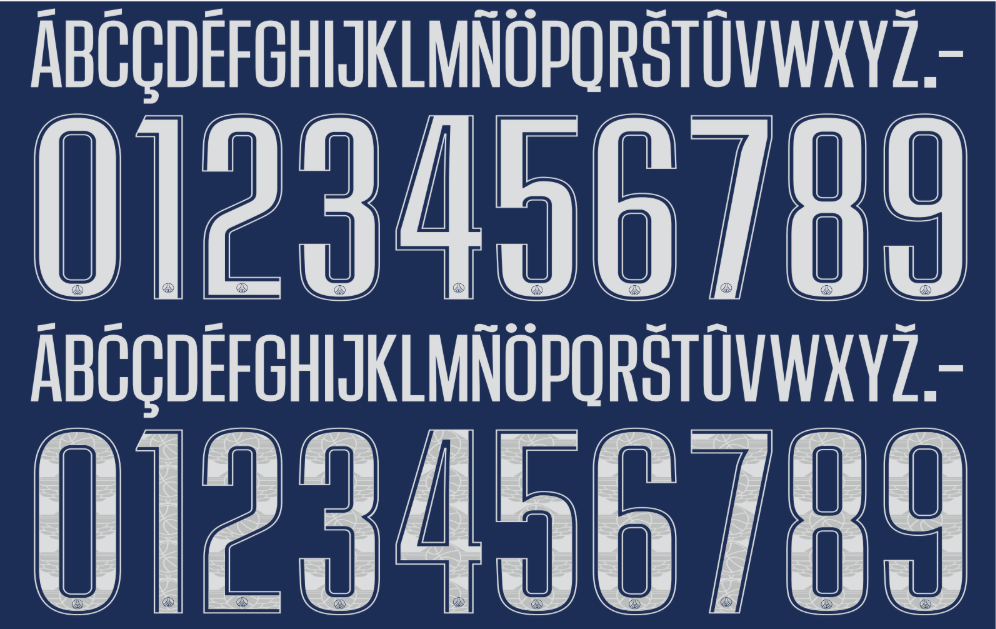
Paris não é apenas a capital da moda, é também o epicentro do estilo no futebol mundial. A nova temporada 2024-2025 traz o Paris Saint-Germain renovado, com uniformes que continuam a ditar tendências graças à poderosa parceria entre o clube, a Nike e a marca Jordan.
Se você trabalha com personalização de camisas, design esportivo ou modelagem 3D, ter a tipografia correta é obrigatório. Neste post, trazemos o arquivo da fonte oficial usada nos uniformes de jogo da Ligue 1 e Champions League, pronta para elevar o nível das suas criações.
Estilo Visual e Aplicação
A tipografia do PSG para esta temporada reflete a fusão entre o luxo e o streetwear, uma assinatura clássica da colaboração com a Nike. A fonte apresenta um design moderno, com caracteres levemente condensados e traços dinâmicos que sugerem velocidade e movimento.
Um destaque visual importante é a legibilidade à distância e o efeito de “recorte” em certos ângulos dos números, inspirados na arquitetura parisiense e na Torre Eiffel. Essa fonte é utilizada tanto no uniforme titular (Home) tradicional com a faixa Hechter, quanto nos kits alternativos assinados pela Jordan Brand. É a escolha perfeita para estampar nomes de craques como Dembélé, Marquinhos ou Vitinha.
Dica de Design: Para um resultado 100% fiel ao original, utilize uma borda (outline) sutil na cor oposta à do preenchimento da fonte, conforme o padrão usado nas costas da camisa de jogo.